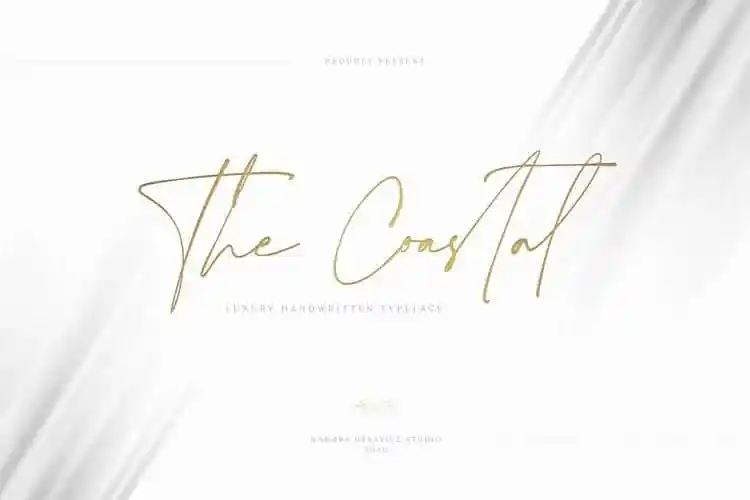
The Coastal Handwritten Font
A fonte The Coastal Handwritten é uma tipografia círculo criada pelos designers do Namara Creative Studio, com uma fidelidade natural que transmite a essência de uma escrita ao vivo. Este é um tipo de fonte de script para uso pessoal e corporativo, perfeito para logotipos, embalagens premium, convites de casamento, websites, citações tipográficas, marcas de água fotográfica, capas de revistas ou livros e projetos onde uma escrita ao vivo com um toque luxuoso é necessário. A fonte The Coastal Handwritten oferece ligaturas e alternativas para criar textos atraentes e diferenciados, tornando-a perfeita para os mais sofisticados e criativos projetos visuais. Descubra como essa elegante fonte pode revolucionar seu próximo projeto visual.